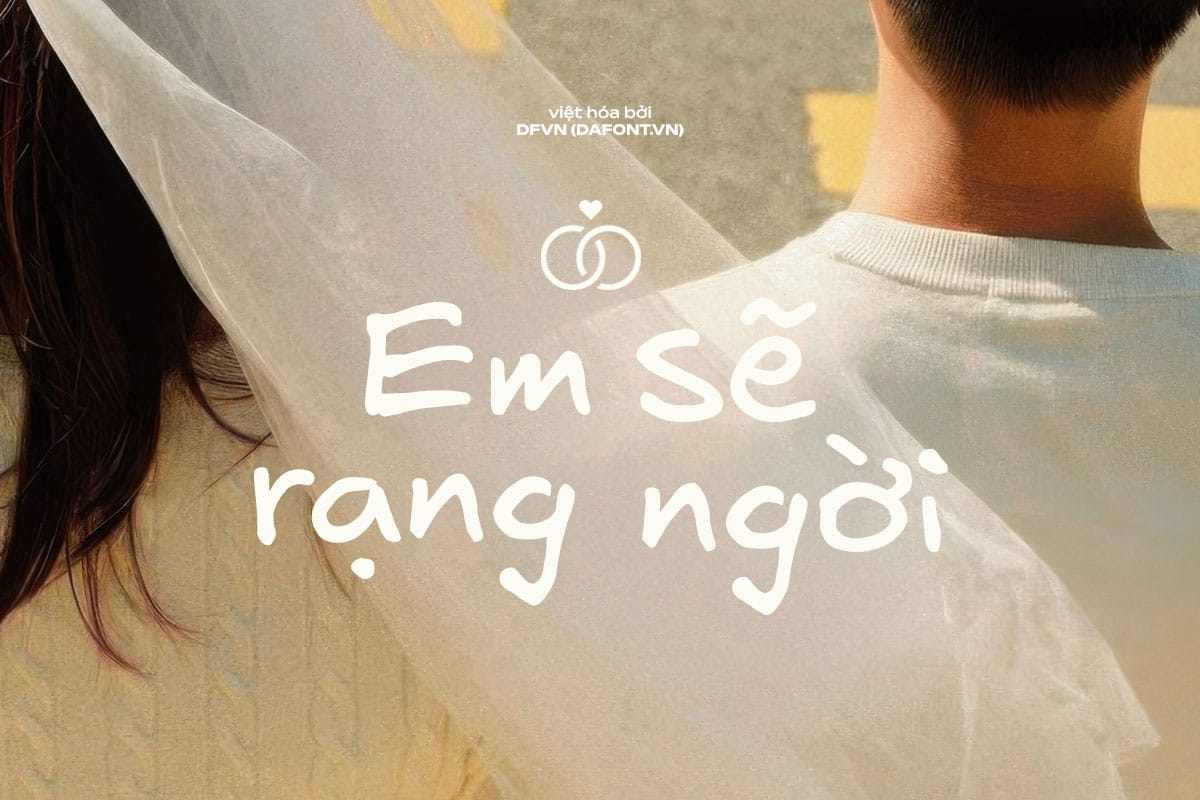
DFVN Excalifont Việt hóa
DFVN Excalifont là font chữ chính thức mới của Excalidraw, được giới thiệu vào năm 2024 nhằm thay thế cho font Virgil gốc. Font này được thiết kế để giữ lại nét viết tay tự nhiên của Virgil nhưng đồng thời cải thiện đáng kể khả năng đọc.
Giới thiệu về DFVN Excalifont
DFVN Excalifont được giới thiệu vào năm 2024, đánh dấu một bước cải tiến so với font chữ Virgil trước đây, vốn là font chữ ban đầu của Excalidraw. Excalifont được thiết kế để giữ nguyên cảm giác viết tay đặc trưng của Virgil, đồng thời cải thiện khả năng đọc, đáp ứng phản hồi từ người dùng về việc Virgil khó đọc trong một số trường hợp. Đây là một phần trong nỗ lực của đội ngũ Excalidraw để nâng cao trải nghiệm người dùng, đặc biệt trong các bản vẽ phức tạp.
Đặc điểm nổi bật
DFVN Excalifont nổi bật nhờ khả năng đọc tốt hơn, giữ được nét viết tay tự nhiên, hỗ trợ đa ngôn ngữ và hoàn toàn mở, miễn phí cho mọi mục đích sử dụng.
• Nguồn gốc: Dựa trên font Virgil viết tay gốc, được tinh chỉnh lại để tăng tính dễ đọc mà vẫn giữ phong cách viết tay tự nhiên.
• Chữ cái hỗ trợ: Bao gồm bộ ký tự Latin (A-Z, a-z) và cả ký tự Hy Lạp (Greek), phù hợp cho nhiều ngôn ngữ khác nhau.
• Mục đích sử dụng: Là font mặc định cho Excalidraw – một công cụ vẽ phác thảo trực tuyến với phong cách vẽ tay, cũng có thể sử dụng cho các dự án bên ngoài.
Excalifont là một phần quan trọng trong trải nghiệm người dùng của Excalidraw, mang lại phong cách viết tay tự nhiên và khả năng đọc tốt hơn so với người tiền nhiệm Virgil. Với giấy phép mở và khả năng tải xuống, nó phù hợp cho cả sử dụng trong Excalidraw và các dự án bên ngoài, mặc dù được tối ưu hóa cho công cụ này.